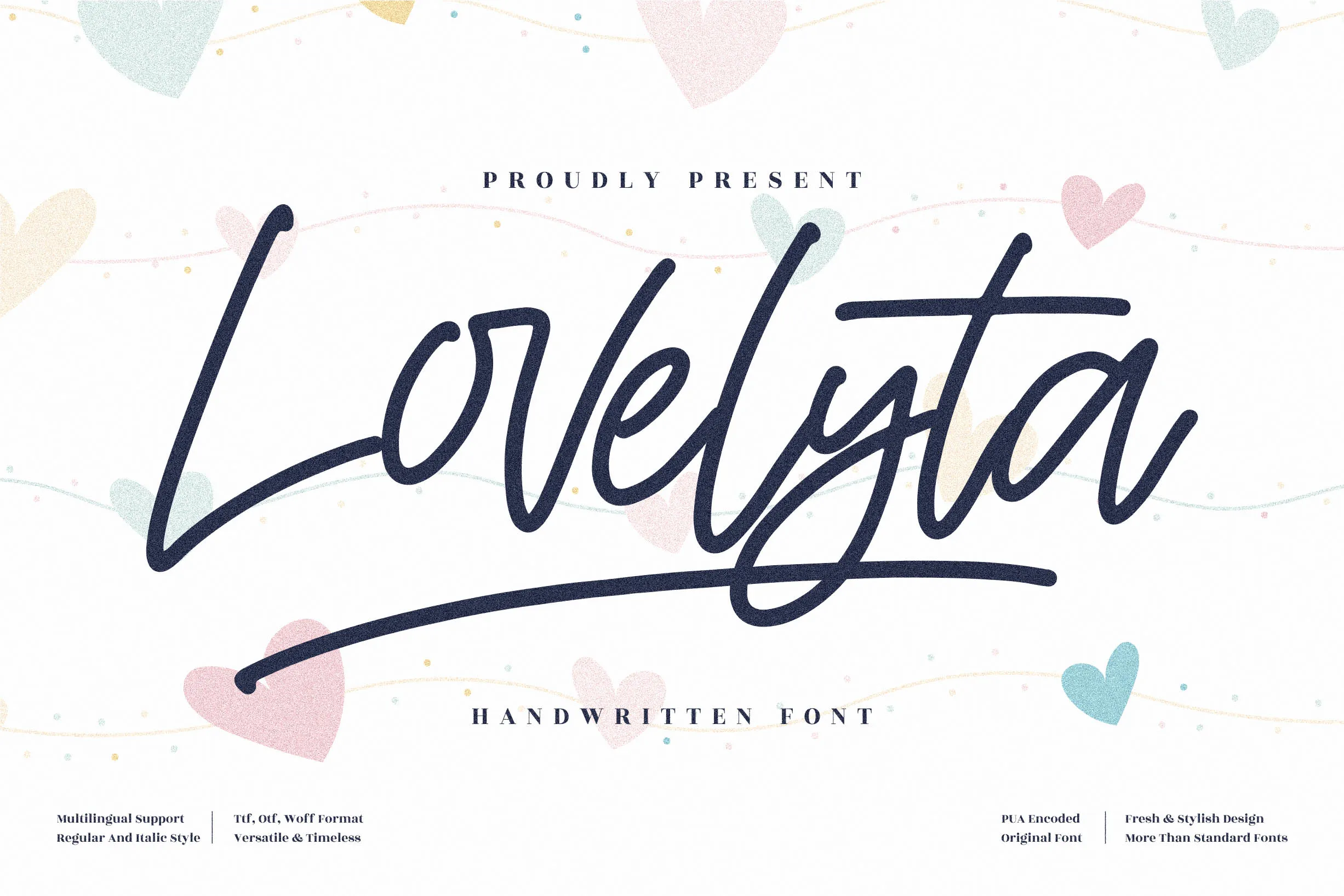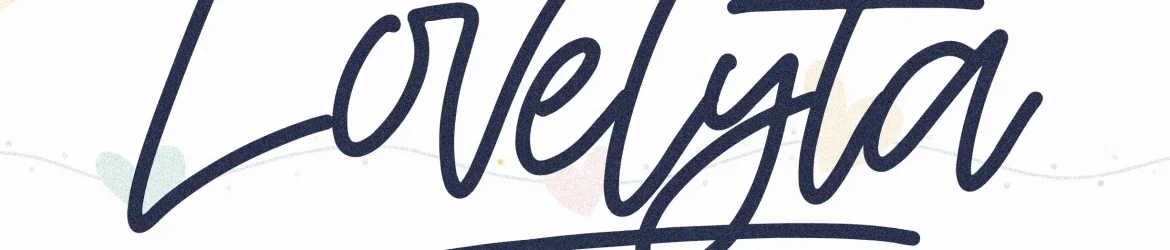
A Lovelyta Font é uma elegante escolha para designers que procuram uma caligrafia manuscrita com delicadeza e profundidade. Ideal para projetos variados, a fonte se destaca por sua versatilidade, desde logomarcas e projetos de marca até capas de livros, nomecards e cartões de convite, tudo isso em um toque autêntico da mão humana. Com seu estilo suave e expressivo, Lovelyta é perfeito para dar vida a designs que exigem uma nota especial. Sujeitos como mugs personalizados, decorações de móveis, embalagens de produtos, etiquetas de produto, até mesmo cartazes e materiais promocionais, ela se adapta e eleva seu estilo ao alcançar um tom mais sofisticado e criativo. Seja para uma pequena marca local ou um projeto maior com um toque personalizado, a Lovelyta é uma ótima escolha para adicionar uma nota de elegância e individualidade à sua produção. Com seu design suave e delicado, você pode garantir que cada detalhe seja único e imediatamente reconhecível. É perfeito para aqueles projetos em que um toque autêntico e humano é o elemento mais desejável.